İş hayatınızda e-posta kullanırken hangi yazı tipini kullanıyorsunuz? E-posta istemcileri yazı tipi konusunda kullanıcıları olabildiğince özgür bırakmaya çalışıyor, ancak önerimiz siz bu yazı tiplerini kullanırken biraz daha dikkatli davranın.
Araştırmaya göre e-posta istemcinizin size sunduğu yazı tipinin dışına çıkmak pek hoş karşılanmıyor. En nötr e-postalar bile, varsayılan yazı tipinden başka bir yazı tipiyse, sinir bozucu olabiliyor.
Kişisel e-postalarınızda istediğiniz yazı tipini rahatlıkla kullanabilirsiniz, ancak iş kurumsal bir düzene girdiğinde yazı tipinin farklı olması bazı rahatsızlıklara yol açabilir.
Herhangi bir durumda mesleki veya önemli bir e-posta yazarken Gmail’in sans serifi, Mac’in Helvetica’sı veya Outlook’un Tahoma’sından yararlanmaya özen gösterin.
Aynı mesajı farklı yazı tipleri ile gönderen araştırmacılar, açık bir şekilde en sade ve okunabilir yazı tipini istemcinin varsayılan fontunda görmüş. Bunun en büyük sebebi karşıdan gönderilen e-postanın isim, tarih, başlık gibi bölgeleriyle aynı olması gerektiğidir. Gelin aynı yazının farklı yazı tiplerinde gönderisini görelim.
Orijinal yazı tipi gördüğünüz gibi son derece sade ve istemcinin diğer yazı stillerine uygun gözüküyor.
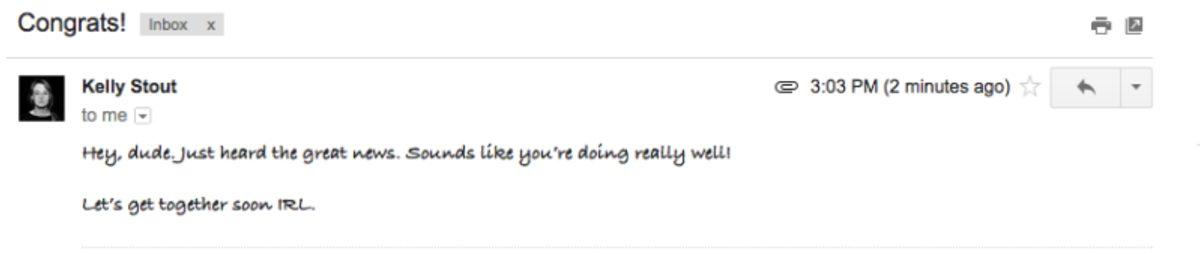
Bu yazı tipi okuyucuyu kısa sürede sıkacaktır. En üstteki orijinal yazı tipinin aksine çok daha zor okuma imkanı sunan bu yazı tipi isim, gönderilme tarihi gibi varsayılan yazılarla uyuşmayarak bu tarz sorunlar ortaya çıkartır.
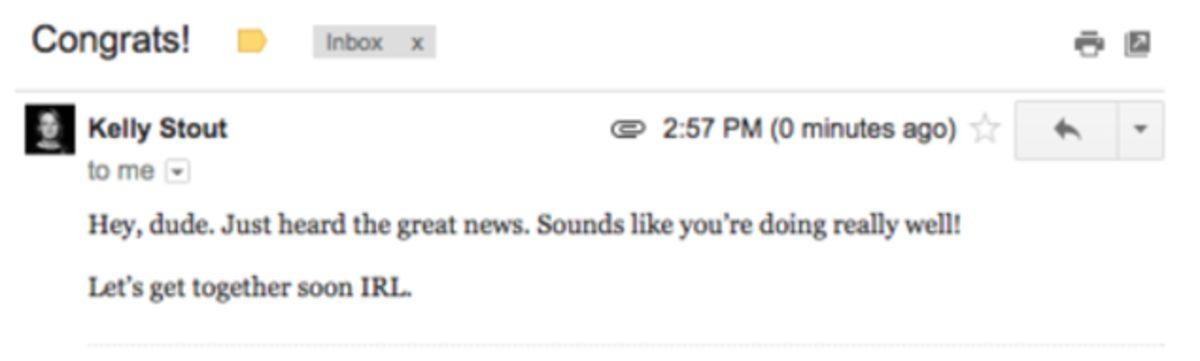
Çok sıkışık olduğu için yine okunurluğu bozuyor. Kullanıcılar bu yazı tipini okurken, özellikle uzun bir yazıysa atlaya atlaya okuyacaktır.
Burada kalın ve küçük bir yazı tipi tercih edilmiş. Daha çok romanlarda gördüğümüz yazı tipi e-postalarda tercih edilmez.
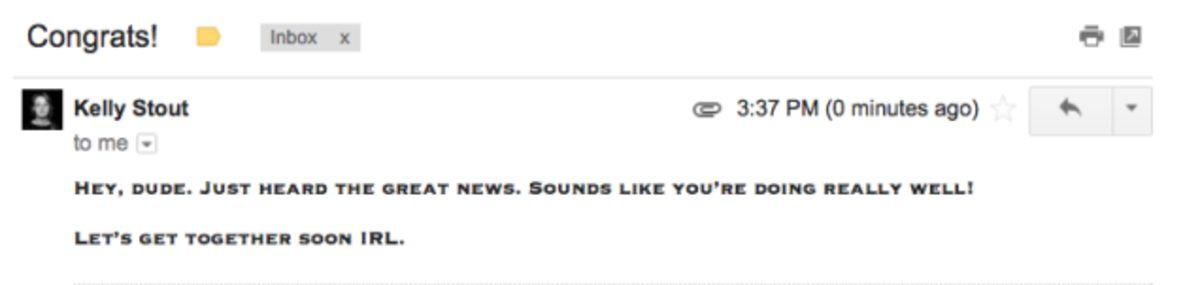
Her harfin büyük olduğu bir yazı tipi. Üstelik kalın. Sakince burada uzaklaşalım.
Bütün bunları geçelim, illa ki yazı tipini değiştireceğim diyorsanız dikkat etmenizi önerdiğimiz birkaç önemli özellik var. Öncelikle yazı tipinin sürekli kalında kalmamasına özen gösterin. Kalın yazı tipi kullanıcıyı çabucak sıkar. Normal yazı tipinizin yanında önemli yerleri kalınlaştırarak vurgulayabilirsiniz.
E-posta veya diğer yazı işlerinde en çok dikkat edilmesi gereken olay, yazı tipinin tırnaklı yapısının olmamasıdır. Tırnaklı yazı tipleri okumayı önemli ölçüde zorlaştırır ve çok yoğun gösterir. Bunun yerine tırnaksız yazılar tercih etmelisiniz. Yine bunlar dışında illa farklı bir font tercih edecekseniz, yazıların rahatlıkla anlaşılabildiği sade ve net yazı tipleri olsun.